Полуустав (шрифт)
Полуустав — форма кириллицы, возникшая во второй половине XIV века. По сравнению с уставом полууставные почерки мельче и округлее.
Типы полуустава
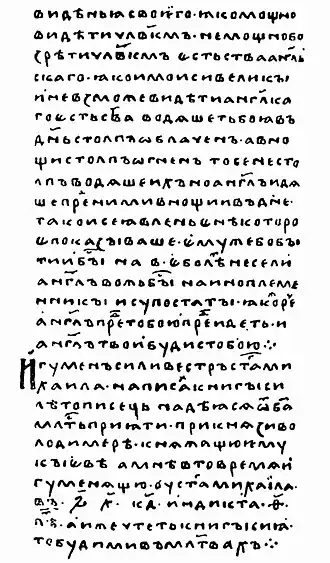
В русском полууставе различают две разновидности: старший (с начала XIV по начало XV века) и младший полууставы. Старший полуустав ещё тесно связан с уставом начала XIV века, сформировался исключительно на русской почве. Его типичным образцом считается почерк второй части Лаврентьевского списка летописи. Младший русский полуустав не восходит к старшему[1]; он, в отличие от старшего, изобилует различными надстрочными знаками, а также отличается употреблением некоторых букв: в нём нет буквы ѥ, используется написание ы (но не ꙑ), активно используется буква ȣ, буквы s и ѳ возможны не только в цифири, ряд букв имеет специфическое начертание[2]. Все эти особенности русского младшего полуустава связаны с подражанием южнославянским полууставным рукописям, проникшим на Русь в XIV—XV вв., после покорения болгар и сербов Османской империей и являются частью процесса Второго южнославянского влияния на русскую культуру[3].
Для заголовков в полууставе применялась особая техника декоративного сочетания букв — вязь.
Эпоха книгопечатания
С появлением книгопечатания в XV—XVI вв. печатный шрифт для русско-славянских книг был отлит по образцу полуустава; таков, например, шрифт русских первопечатников Ивана Фёдорова и Петра Мстиславца, выпустивших в Москве в 1564 году первую печатную книгу — «Апостол». Русский полууставный шрифт употреблялся в церковных и гражданских печатных книгах вплоть до 1708 года, когда по указу Петра I для гражданских книг устанавливается новый гражданский шрифт, а прежний церковный шрифт остаётся только для книг духовного содержания.
Образцом современного полуустава может служить шрифт Ирмологион.